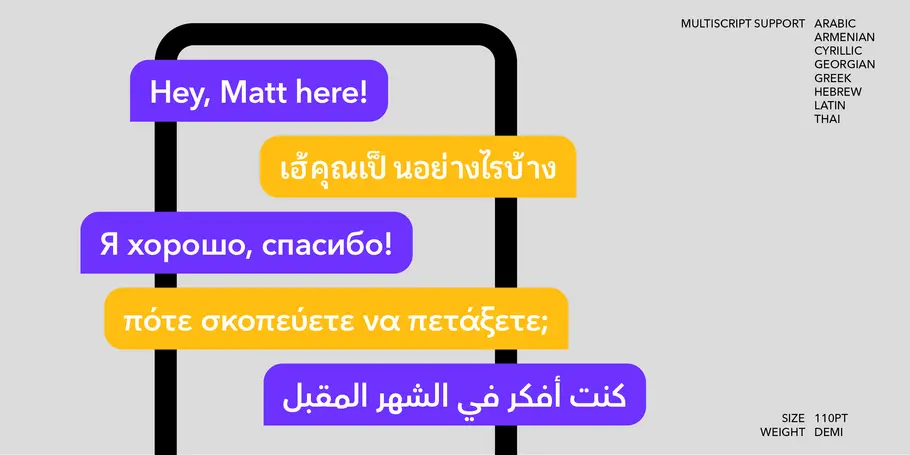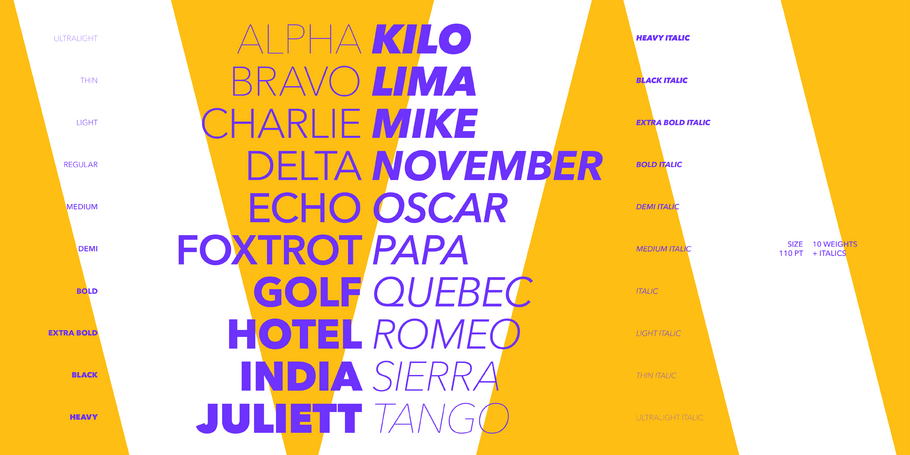
Avenir® Next World
Le design au-delà des frontières.
La famille Avenir Next World, dernière parution de Monotype sous la direction d’Akira Kobayashi, est une famille de polices étendue qui prend en charge plus de 150 langues et écritures. Parce qu’il est profondément familier des itérations existantes des designs Frutiger, et par sa compréhension même de la philosophie du designer, Akira était particulièrement qualifié pour mener à bien l’ajout de nouvelles langues à cette famille.
Avenir Next World rassemble 10 graisses, de UltraLight à Heavy. Les 10 styles d’italiques respectifs ne sont pas compatibles avec l’arabe, le géorgien et le thaï, car l’italique n’est pas usuel dans ces écritures/langues. Pour ceux qui n’ont pas besoin d’une prise en charge complète des langues, des produits non latins séparés, concernant seulement l’écriture arabe, cyrillique, géorgienne, hébraïque et thaïlandaise, sont également disponibles.
« Avenir est un choix judicieux pour les marques depuis des années. Avec son apparence discrète, elle correspond aux produits et aux marques ayant une image claire et ouverte. Pour ne pas détourner des textes l’attention du lecteur, la forme des lettres est extrêmement soignée », explique Akira, qui a dirigé l’équipe de design typographique pour ce projet.
Avenir Next World.
La typographie originale d’Avenir a été créée en 1988 par Adrian Frutiger. Son nom "Avenir", projeté vers le futur, laisse entendre l’influence de Futura dans le design. Mais, à la différence de Futura, Avenir n’est pas uniquement géométrique. Ses traits verticaux sont plus épais que les horizontaux, le "o" n’est pas un cercle parfait, et les ascendantes sont raccourcies.
Ces nuances facilitent la lisibilité et donnent à Avenir une apparence harmonieuse et adaptée aux textes comme aux gros titres. En 2002, Akira Kobayashi a travaillé aux côtés d’Adrian Frutiger pour donner vie à Avenir Next. Ce qui devait être une simple reprise de l’original est devenu une famille sans serif réellement supérieure, avec des standards techniques surpassant de loin le statu quo. Cette mise à jour proposait une vaste extension du concept original, avec l’ajout de styles allant de l’Ultra Light au Heavy.
Dans cette collection de 32 polices, les condensées ont défié toute concurrence sur le marché des sans en terme de lisibilité à l'écran et hors écran — et ce, quelle qu’en soit la taille. Elle comprenait aussi des graisses plus épaisses faisant d'excellentes polices d'affichage à part entière, capable de s’associer à de nombreuses typographies de texte contemporaines avec serif.
Le design Avenir Next a connu une immense popularité depuis sa sortie. La police de caractères a tout de suite été un succès en impression et, grâce à sa palette étendue de caractères et son optimisation spécifique, a connu le même succès sur les écrans. De nombreuses entreprises l’ont adoptée tant pour leur documentation officielle que pour des logotypes.
La famille Avenir Next World, dernière parution de Monotype sous la direction d'Akira Kobayashi, est une famille de polices étendue qui prend en charge plus de 150 langues et écritures. Parce qu’il est profondément familier des itérations existantes des designs Frutiger, et par sa compréhension même de la philosophie du designer, Akira était particulièrement qualifié pour mener à bien l’ajout de nouvelles langues à la famille.
Avenir Next World rassemble 10 graisses, de UltraLight à Heavy. Les 10 styles d’italiques respectifs ne sont pas compatibles avec l’arabe, le géorgien et le thaï, car l’italique n’est pas usuel dans ces écritures/langues. Pour ceux qui n’ont pas besoin d’une prise en charge complète des langues, des produits non latins séparés, concernant seulement l’écriture arabe, cyrillique, géorgienne, hébraïque et thaïlandaise, sont également disponibles.
Creative Type Director Akira Kobayashi has three decades of experience, with an extensive background in Japanese typeface design and a deep understanding of calligraphy. After studying at Musashino Art University in Tokyo for four years, Akira Kobayashi accepted his first job at phototypesetting manufacturer Sha-Ken Co., where he was involved in the lengthy and intricate process of designing Japanese fonts.
Akaki Razmadze is from Tbilisi, Georgia. During his studies, he completed an internship at Monotype (Bad Homburg, Germany), where he worked to develop Georgian versions of various Monotype’s typefaces; among them were Helvetica, Meta and so on.